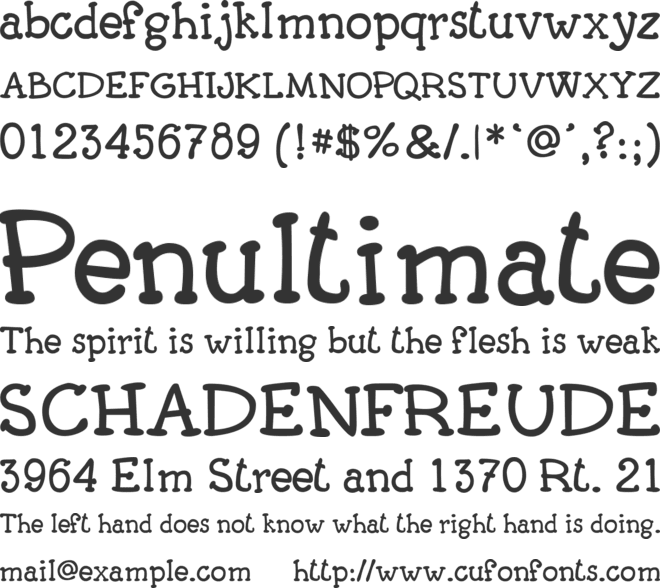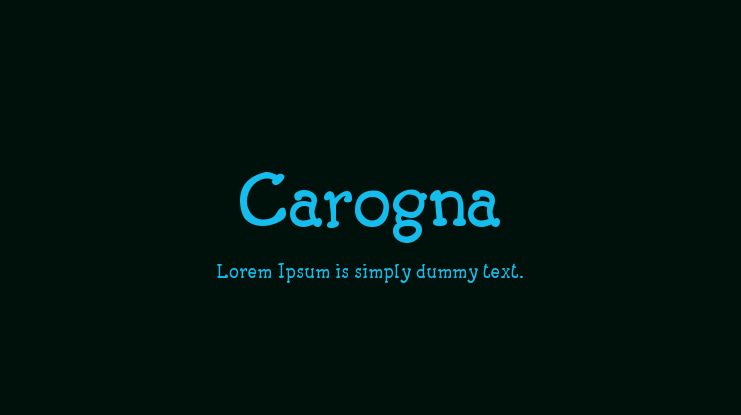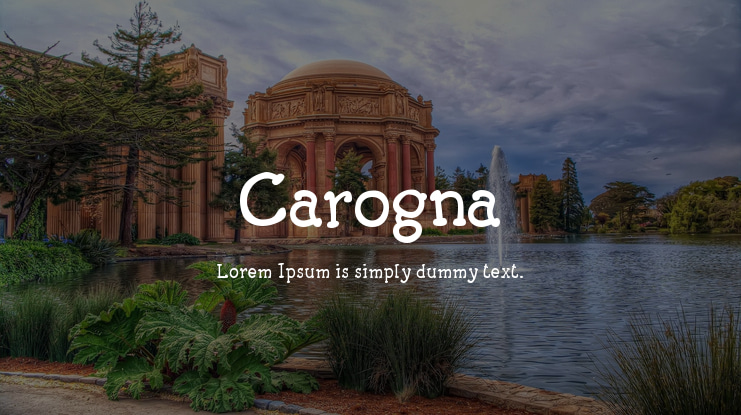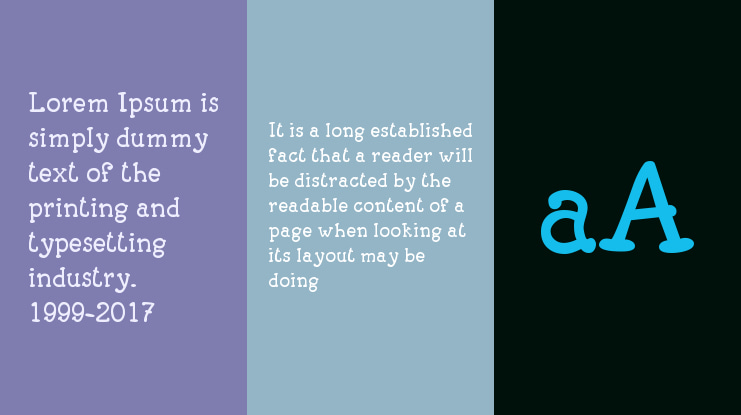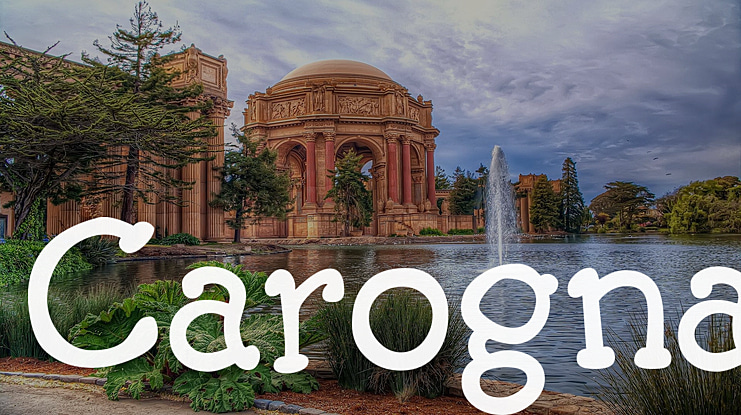
Carogna Font
Il font Carogna è stato realizzato nel 1996 per il mensile di satira L'Eco della Carogna, diretto da Angese. Il font Carogna era utilizzato nei titoli e nei testi degli articoli.